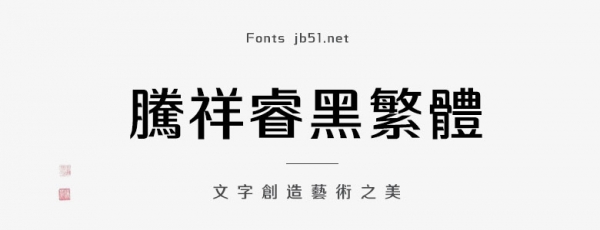
騰祥睿黑繁體合集(W1/W2/W3/W4)是一款不錯(cuò)的藝術(shù)字體,由騰祥字庫(kù)出品,該系列字庫(kù)字形結(jié)構(gòu)端正,重心平穩(wěn)。橫豎筆畫(huà)挺拔,軟筆畫(huà)細(xì)膩,適合應(yīng)用于藝術(shù)設(shè)計(jì)、平面宣傳設(shè)計(jì)、網(wǎng)頁(yè)設(shè)計(jì),書(shū)法字帖等領(lǐng)域,需要的朋友可以前來(lái)本站下載。
騰祥睿黑系列字庫(kù)是騰祥公司自主精心設(shè)計(jì)開(kāi)發(fā)的黑體系列字庫(kù)。該系列字庫(kù)字形結(jié)構(gòu)端正,重心平穩(wěn)。橫豎筆畫(huà)挺拔,軟筆畫(huà)細(xì)膩、柔美。黑白均勻、行文貫通。筆畫(huà)精致、簡(jiǎn)潔清晰。塔形頓點(diǎn)、撇點(diǎn)和部分折筆處外圓角的設(shè)計(jì),使得字形看上去內(nèi)斂、圓潤(rùn)、弱化了黑體尖銳和張揚(yáng)的感覺(jué)。